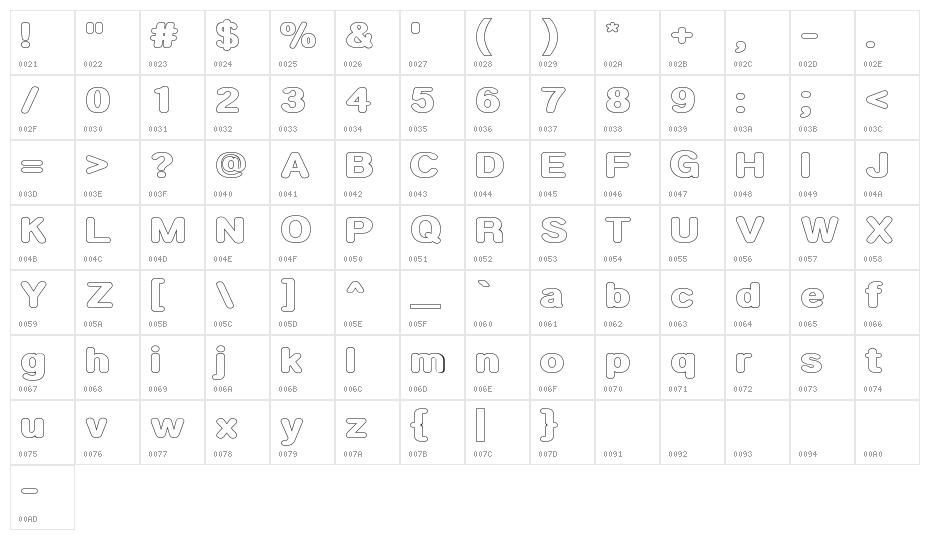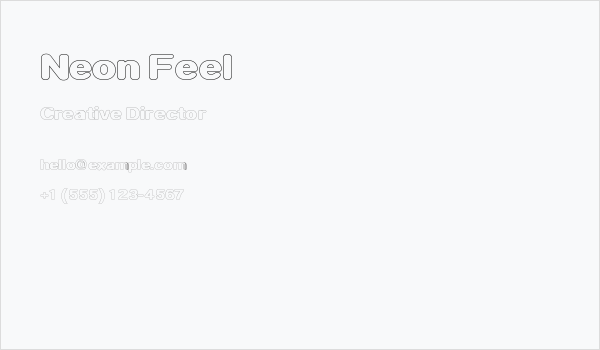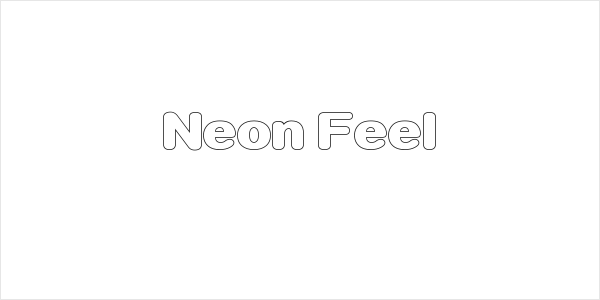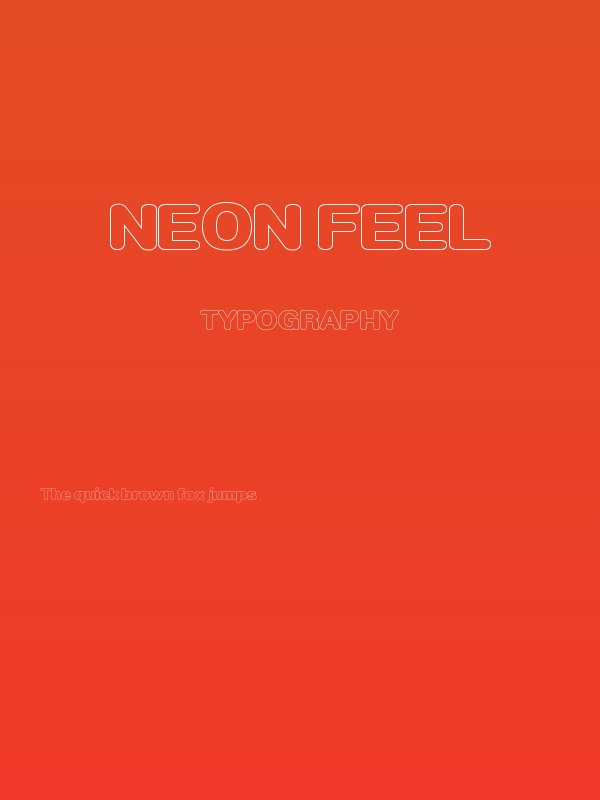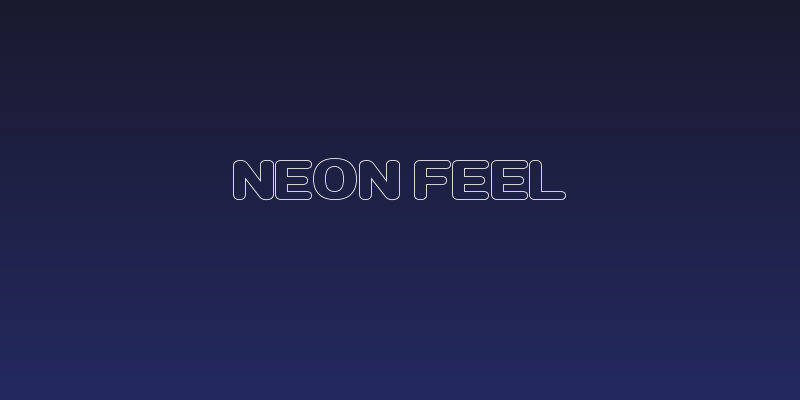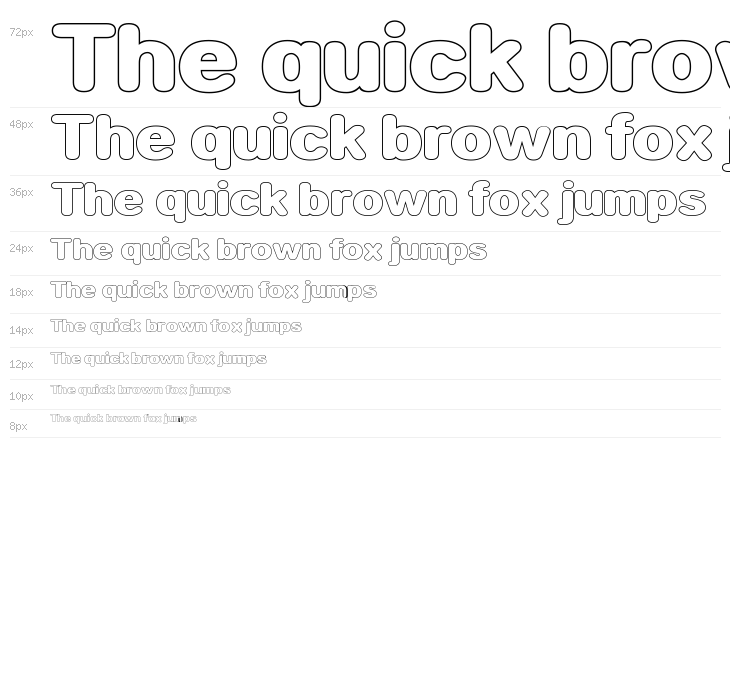
Neon Feel Font
| Anwendungsfall | Headlines, Logos, Signage |
| Vorgeschlagene Projekte | Ideal for neon signs, digital artwork, branding, and advertising materials that require a modern and eye-catching font. |